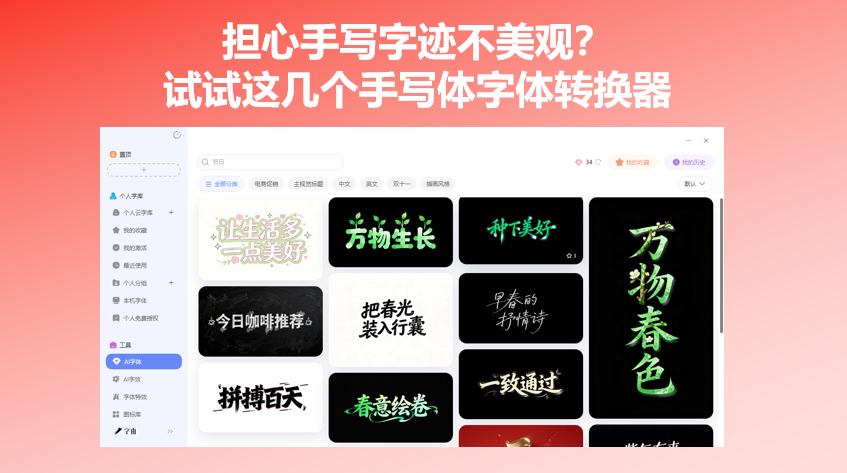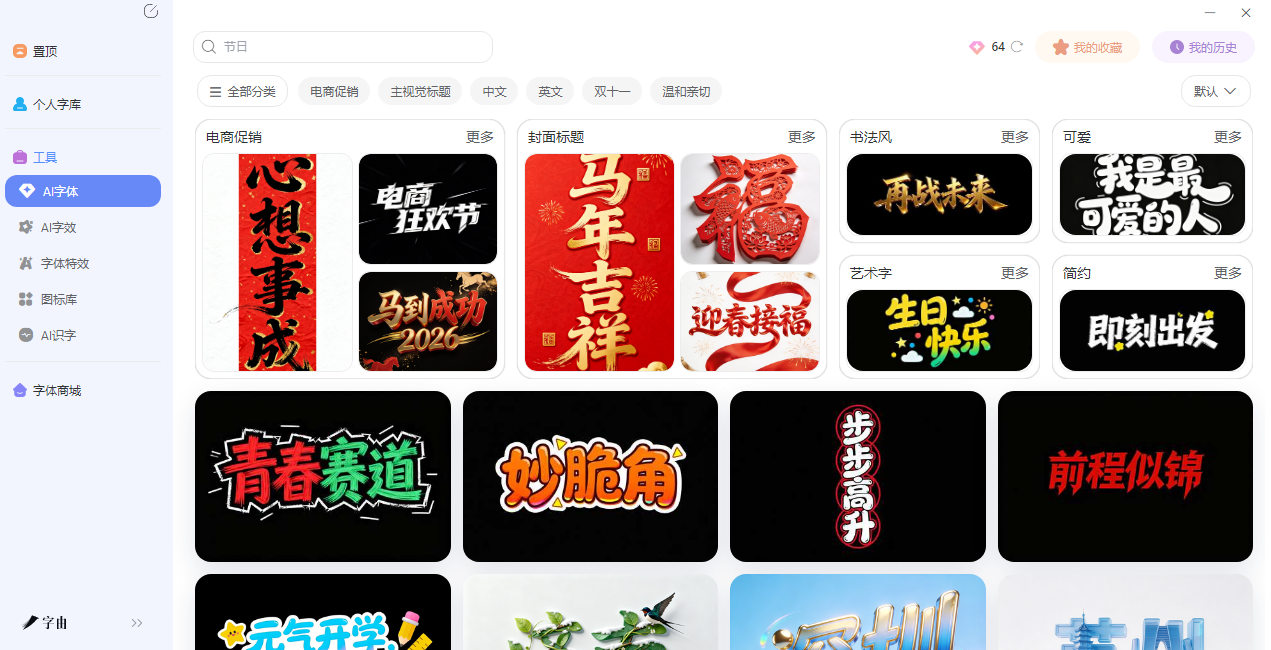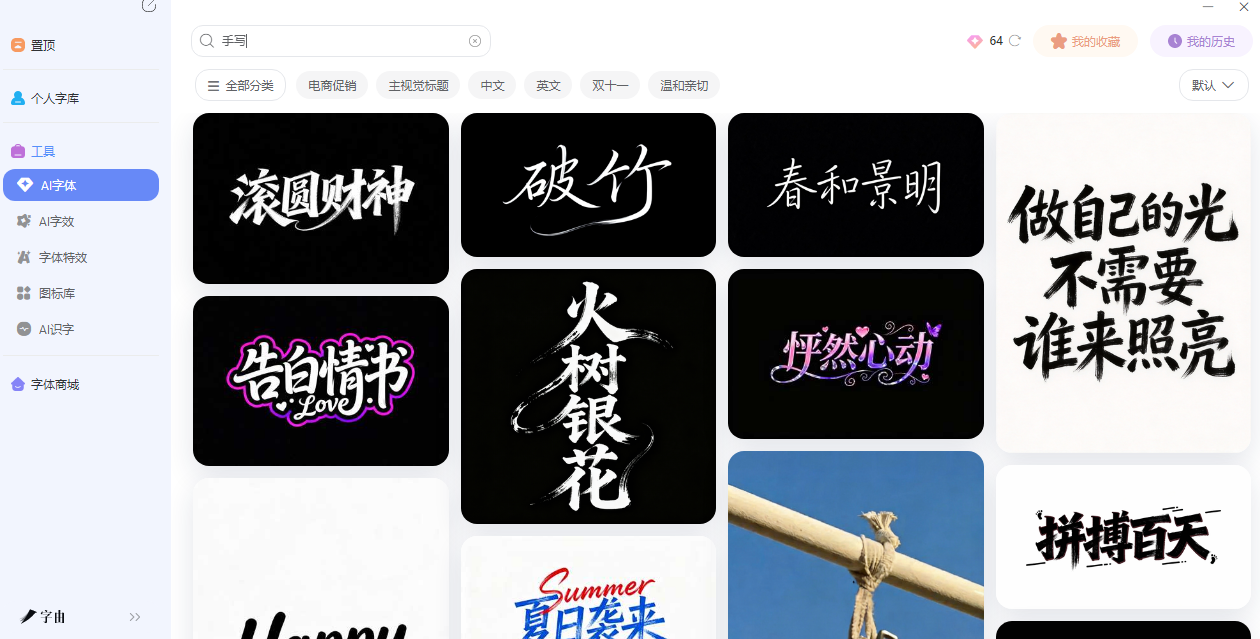
担心手写字迹不美观?试试这几个手写体字体转换器
如果你喜欢做手账的话,肯定会试着写一些字让画面变得丰富起来的句子或者单词,但是明明排版和配色都搞定了,结果自己写的字歪歪扭扭,一下子拉低了整页的观感,给朋友写贺卡,想表达心意,字迹却拿不出手。做作业或笔记,手写的速度永远跟不上思路。以前我们可能会为这些事情苦恼,但是现在有专门的手写体字体转换器,把打好的文字放进去,几十秒就能变成逼真的手写效果。今天我就来介绍几个手写字体转换神器,喜欢的可以收藏先码住。
很多人知道字由是字体网站,上万款字体可供使用。但你不知道的是,字由的“AI字体”功能,本身就是一款超级好用的手写体字体转换器。你不需要下载任何字体,也不用装软件,打开网页就能用。
以前想要手写感,你得先去字体网站翻,找到一款手写体,下载、解压、安装,然后打开PS,打字,看效果。如果不满意,再重复一遍。光试字体就能耗掉半天。更麻烦的是,很多手写体字体有版权问题。
字由的AI字体功能,把“找手写体”变成了“选手写模板”。你不用下载任何东西,直接在网页里输入文字,选一个手写风格的模板,点一下生成,几十秒就出图。而且生成的是透明背景的PNG,直接拖进PS、剪映、Canva里就能用。
下面我会教大家如何使用字由来生成AI手写字体:
- 第二步:搜“手写”。进入页面后,你会看到很多模板。在搜索框里输入“手写”,系统会自动筛选出所有手写风格的模板。比如“手写体”“毛笔字”“钢笔字”“儿童手写”“浪漫花体”……几十种风格摆在你面前。
- 第三步:选一个顺眼的模板。每个模板都有预览图,鼠标放上去就能看到效果。你可以先挑两三个看着喜欢的,记下来。
- 第四步:输入你的文字。点进一个模板,点击“做同款”。在输入框里填你想生成的文字,比如“春日来信”“见字如面”“生日快乐”。注意:最好和模板的字数保持一致。模板是四个字,你就填四个字;模板是两个字,你就填两个字。这样生成的效果最自然。
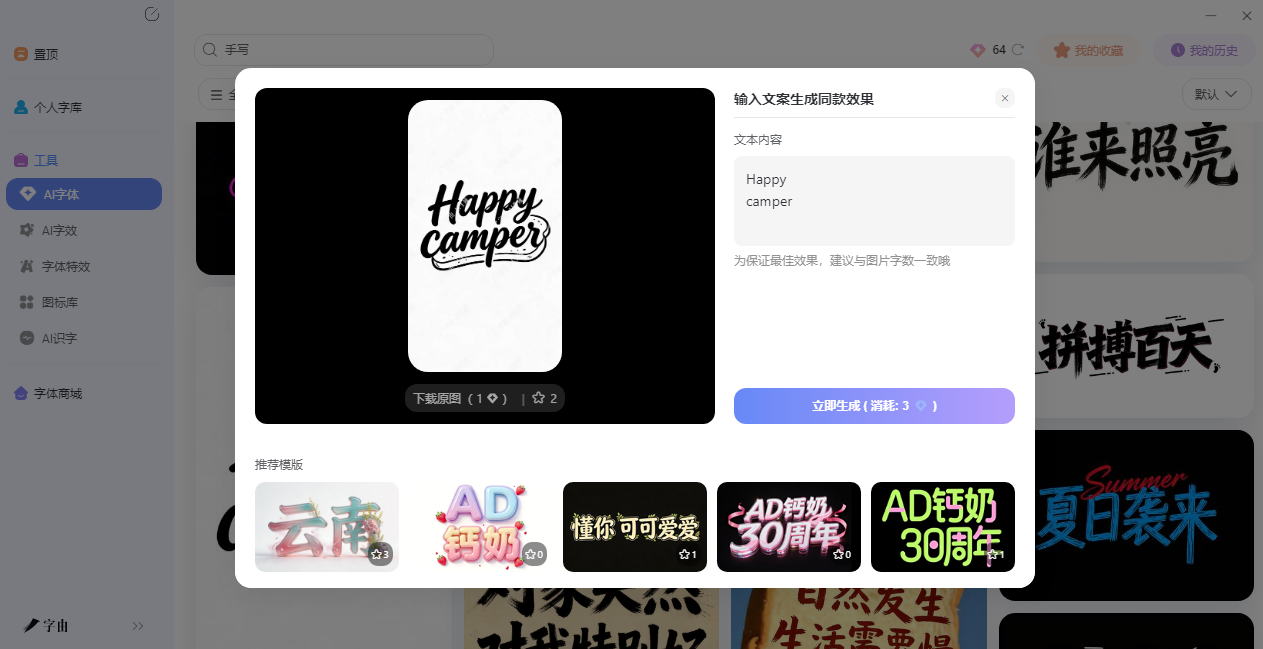
- 第五步:点一下生成。确认文案后,点击“立即生成”。等20-30秒,系统就会输出一张高清的手写艺术字图片。生成后可以预览,不满意就换其他模板再试。
- 第六步:下载,直接用。生成满意后,点击下载。下载时有两个选项:带背景的可以直接用,透明背景的更方便后期排版。我一般选透明背景,直接拖进PS或者剪映里,不用抠图,不用调色。
虽然说市面上也有很多其他的手写字体转换器但是字由有几个独特的优势:很多工具只能让你在线预览,下载要收费,或者有水印。字由不仅免费,还直接标注了每款字体的授权类型,你用的时候完全不用担心侵权。而且它不需要你安装任何软件。 打开网页就能用,如果你不想要特效,只是想用现成的手写体,字由的免费商用字体库里也有几百款手写体,随便挑。
2、Text To Handwriting
这个工具功能很全面。它支持输入文字,转换成手写体,而且可以生成多页文档。输入文字后,你可以选8种不同的手写字体,调整字体大小、墨水颜色、行间距。还能选纸张样式,比如白纸、横格纸、方格纸。支持导入PDF和DOCX文件,直接把文档转成手写体。它还能生成手写的数学公式,做作业或者学术笔记的时候很实用。生成后可以下载为PNG图片,也可以导出为PDF。实时预览功能也很方便,调参数的时候能看到效果变化。
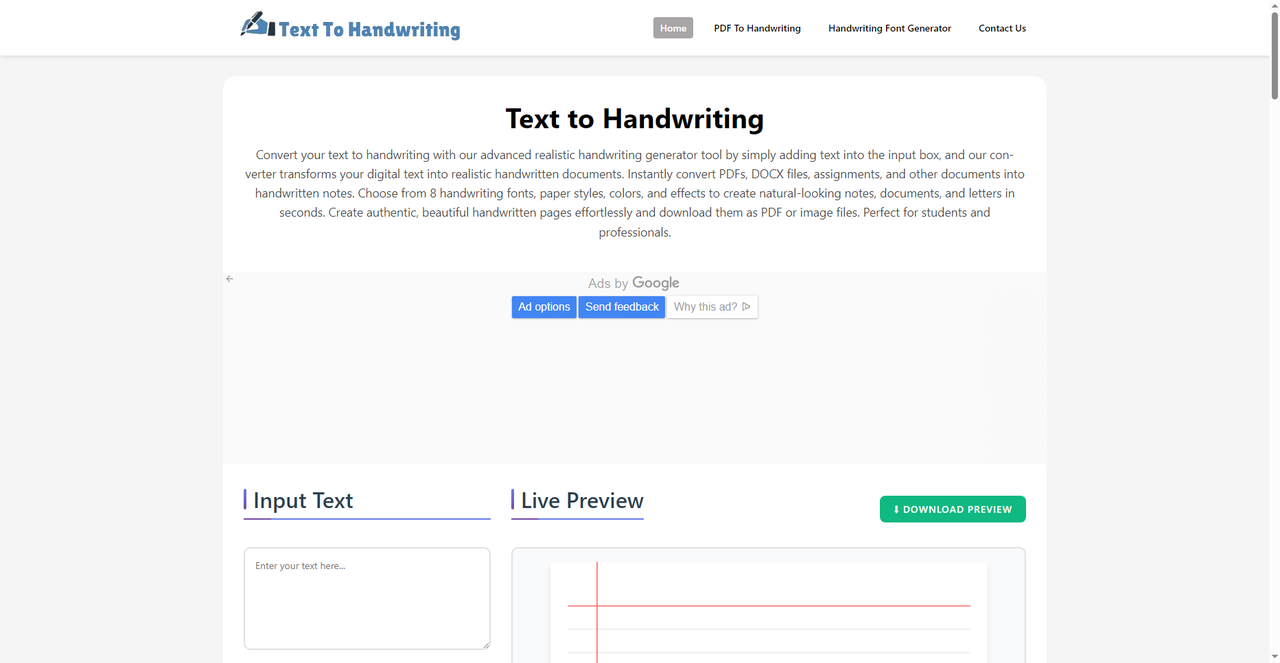
3、TXT TO HANDWRITING
这个工具功能更强大。它支持导入PDF、DOCX文件,直接转换成手写体。可以调整字体大小、行高、字间距、段落间距,还能加阴影效果。特别的是,它支持数学公式转换,能把打好的数学公式变成手写体。做学术论文、作业的时候很实用。纸张尺寸可选A4等标准尺寸,横版竖版都能调。生成后可以保存为JPG 或PDF。还提供了视频教程,不会用的话可以看教学。
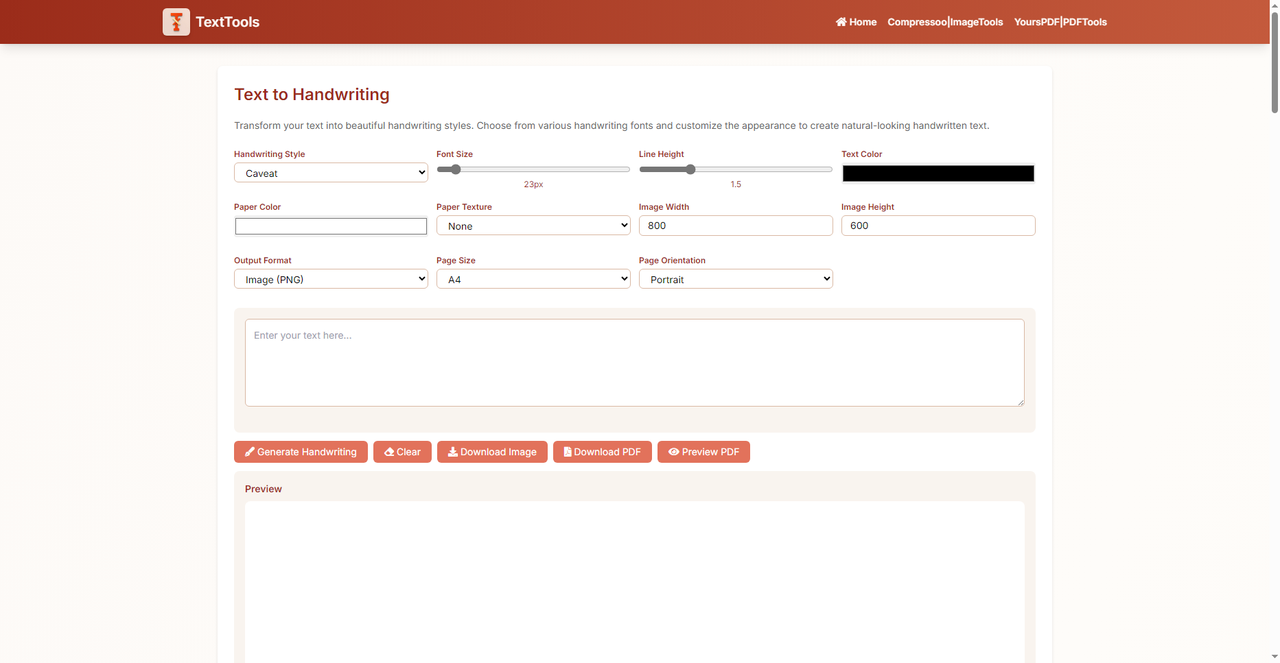
4、TXT TO HANDWRITING
这个工具是中文界面,操作起来很顺手。它最大的特点是所有处理都在浏览器本地完成,不上传服务器,保护隐私。输入文字后,可以从9款手写字体里选,还能选纸张样式(空白、横线、点阵)。可以调整墨水颜色和粗细,生成的效果很逼真,有基线抖动、倾斜、墨水浓淡变化,看着就像真的手写。支持最多6 页内容,生成后可以保存为PNG图片,也可以合并成PDF。完全免费,不用注册。如果你比较在意隐私,不想把文字上传到服务器,这个工具很合适。
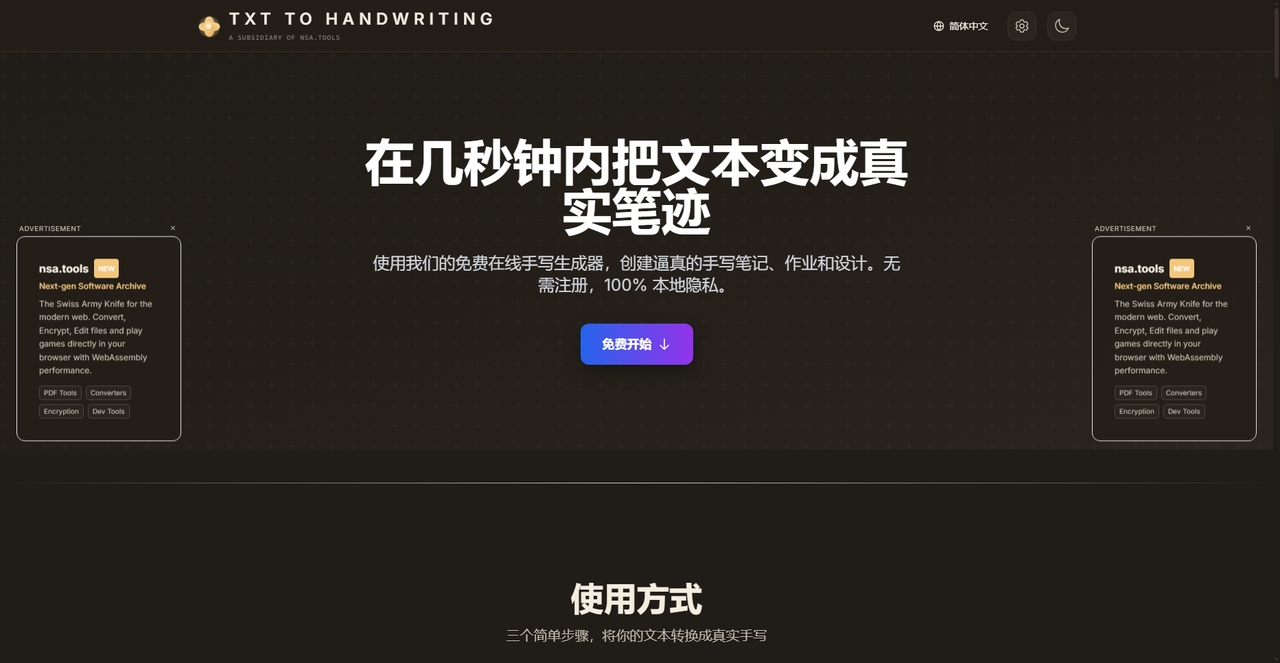
5、Transform Your Text into Handwriting
这个工具是我第一次用的那个,也是功能很全的一个。它的页面分左右两栏,左边是输入和调节区,右边是实时预览。
输入文字后,可以选手写字体、调整字号、行距、字间距、段落间距。纸张背景可以选横线、点阵、方格,还能选纸张颜色。最特别的是它可以设置“阴影效果”,让文字看起来像是写在有厚度的纸上。
它还支持“镜像纸”功能,偶数页的纸张背景可以翻转,做双面打印的时候很实用。生成后可以保存为JPG或PDF,还能预览效果。参数调节非常细,适合对效果有要求的用户。
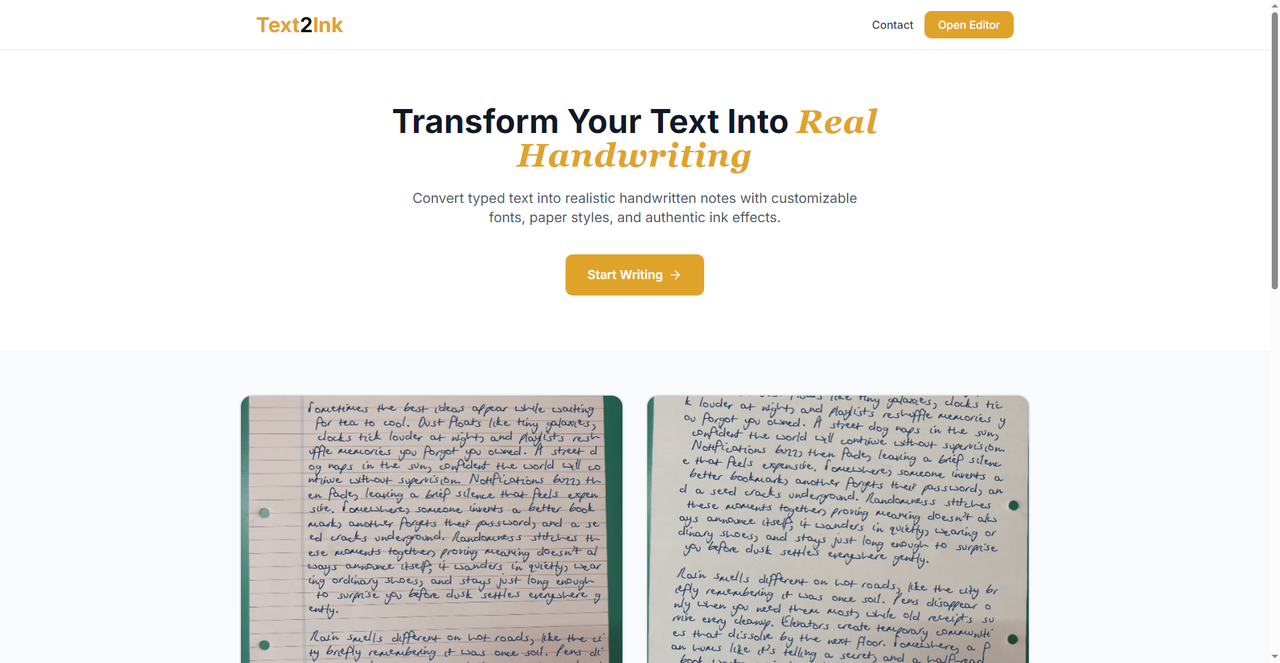
6、手写体转换器
最后一个工具也是一个综合性的手写体转换器,它提供了多种纸张背景,比如普通的白纸、复古的牛皮纸、带纹理的宣纸等。输入文字后,可以选手写字体、调整字号、行距、字间距,还能选墨水颜色。纸张背景可以选横线、点阵、方格,还能上传自定义背景图片。生成后实时预览,效果满意了再下载。支持导出PNG和PDF。纸张纹理很丰富,做复古风格的信件或者文艺类的设计很合适。